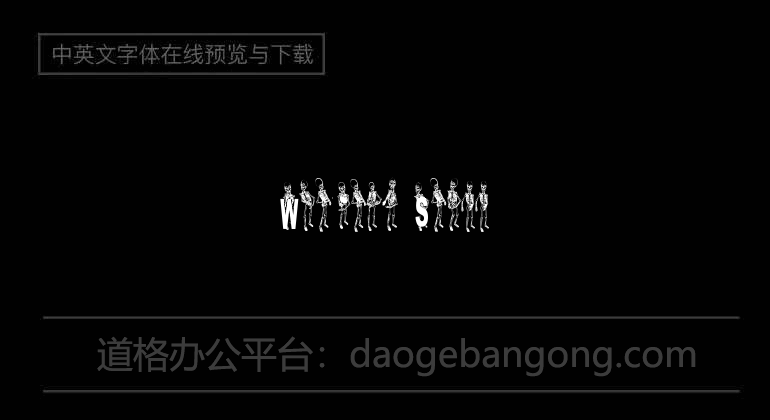
Witches Stuff 是一种手绘风格的字体,具有非常浓重的奇幻和神秘气息。这种字体的特点是线条流畅,具有手工感,字母之间距离较小,形成了一种紧凑的排版效果。此外,该字体的字母外形不规则,形成了一种独特的风格,使其非常适合用于魔法、巫术、神秘、古老或奇幻主题的设计。这种字体可用于海报、书籍封面、游戏、电影、网站等多种设计应用。内容介绍
Witches Stuff是一款非常不错的手写艺术字体,具有很好的视觉感,适合于文化类的宣传设计、商业类品牌的广告和产品包装设计以及个性化文字排版等较多场景。